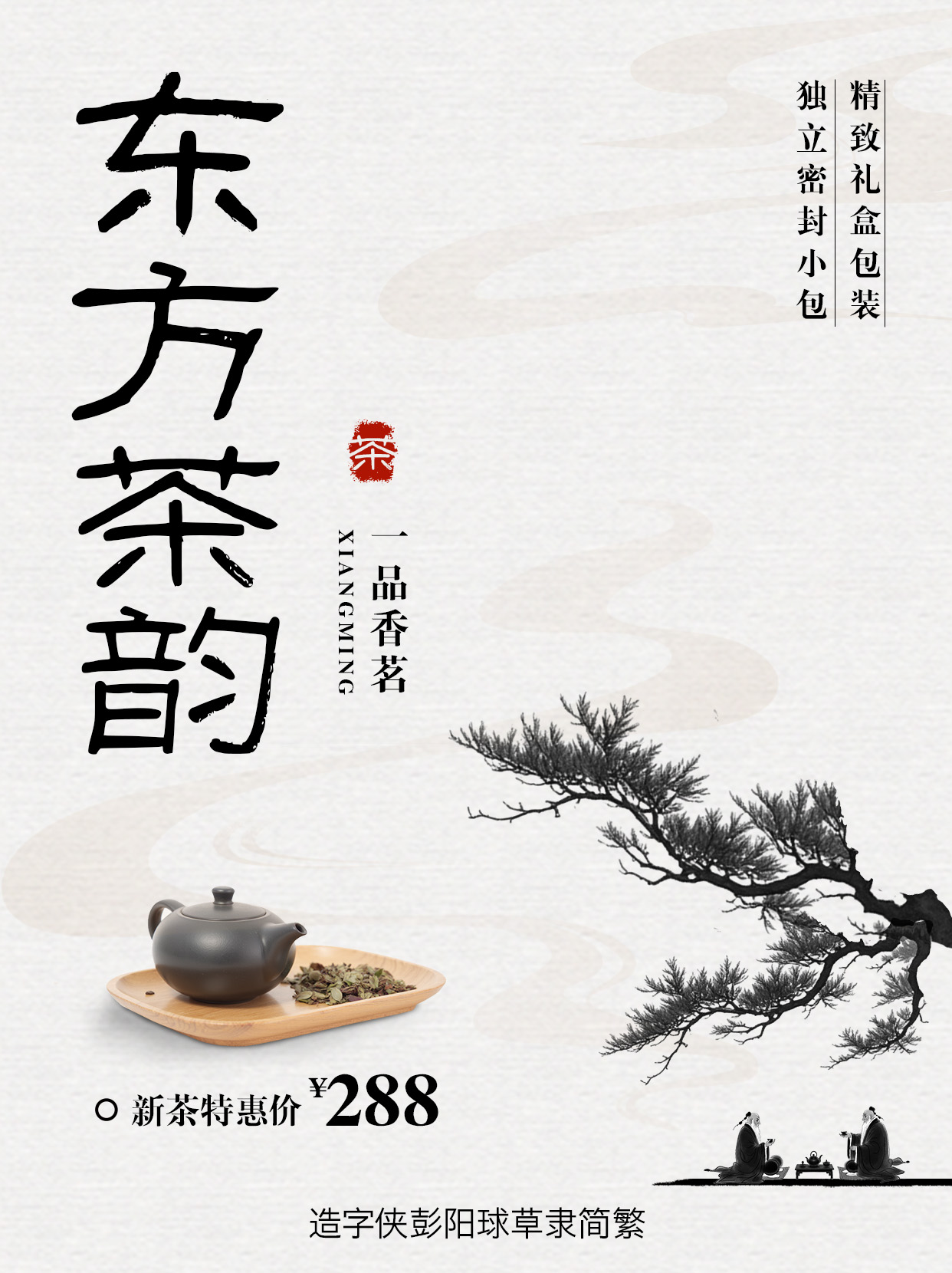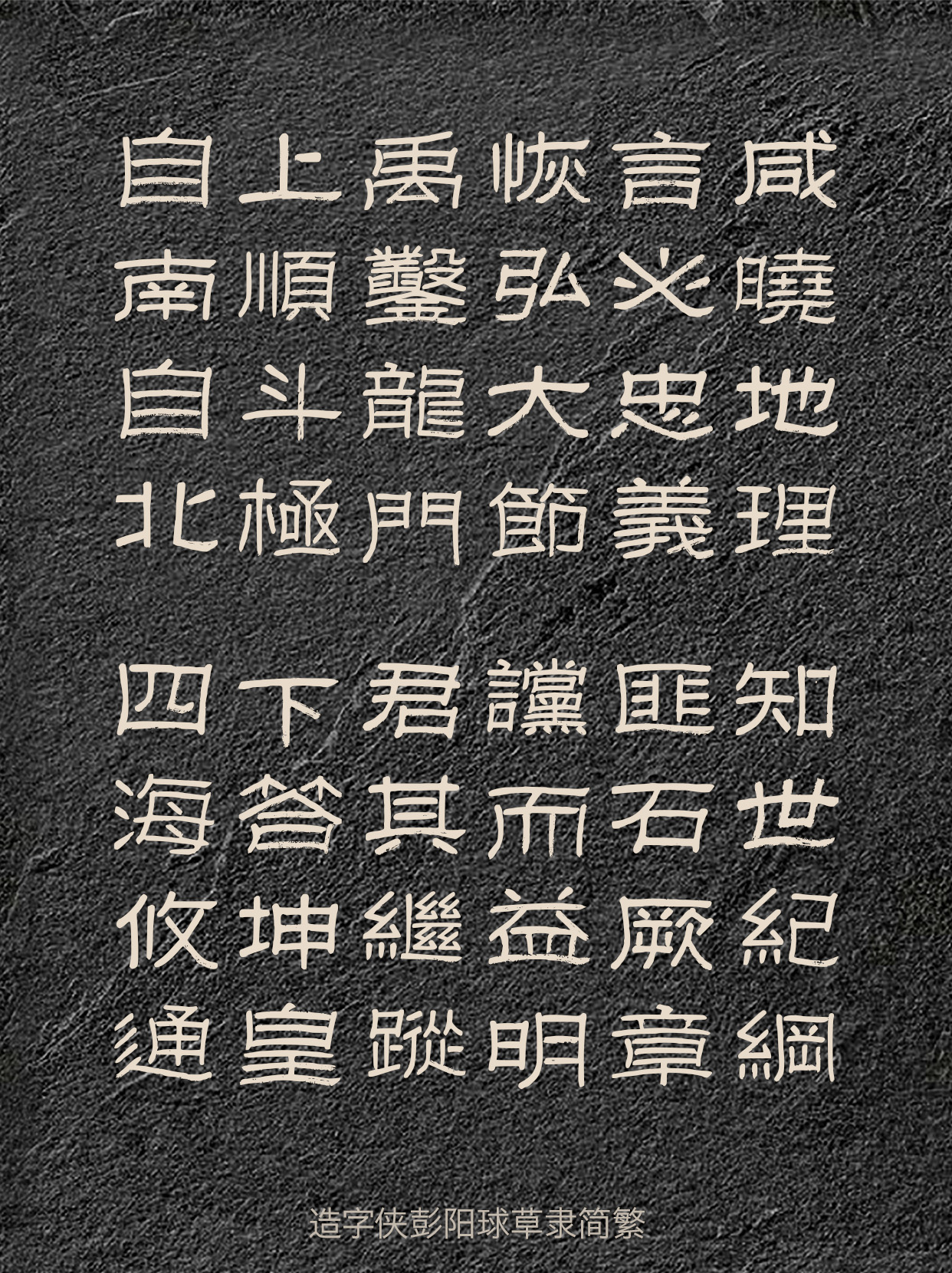
造字侠彭阳球草隶简繁
PlayFont-CaoliGBT
路出玉门关,城接龙城坂
造字侠彭阳球草隶简繁是一款古朴洒脱的书法字体,取法东汉《石门颂》之雄强开张,融入草书流动笔意。这款字体结体疏朗,中宫宽博,笔画波磔有韵、飞白自然,同时符合现代用字规范,适合作为标题字体用于书籍封面、展览海报、文化品牌及茶酒包装等场景,可以营造出苍茫古朴又飘逸洒脱的人文气质。